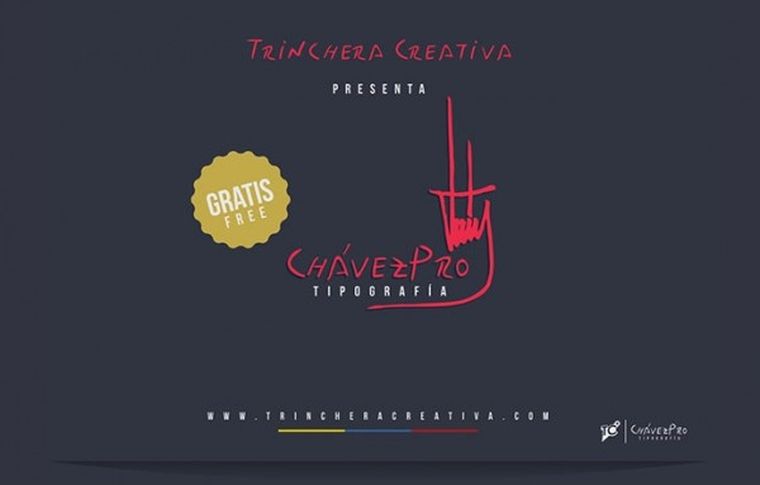
Idolatría: crearon una fuente tipográfica con la letra de Chávez
El fallecido presidente de Venezuela Hugo Chávezhabría cumplido hoy 60 años y sus seguidores se empeñan en mantener vivo su legado, ideas e incluso presencia. Algunos de ellos han deseado tanto que su líder continúe escribiendo que han desarrollado una tipografía inspirada en el ex presidente venezolano.
La fuente TC ChávezPro ya puede incorporarse al menú de cualquier procesador de textos convirtiendo el nombre del denominado líder bolivariano en una más de las opciones de escritura del menú junto a los clásicos Times New Roman o Arial, según lo publicó en su portal digital el diario peruano El Comercio.
La idea surgió de un grupo chavista denominado Trinchera Creativa, un colectivo que ofrece la opción de descargar la fuente desde supágina web.
La tipografía imita la letra del zurdo político, cuya firma es ya parte habitual en camisetas, gorras, llaveros y cuanto artilugio publicitario se vende en Venezuela con su imagen. Cabe resaltar que la comercialización de objetos relacionados con el promotor del Socialismo del Siglo XXI es más que prolífica.
Y para ese tipo de proyectos, esta nueva letra será una ayuda inestimable, según indicó el diseñador Marco Volpe, creador de la fuente. Volpe aseguró que quiso hacer un regalo a los seguidores deChávez en su cumpleaños y también a quienes trabajan con su imagen.
"La idea más que todo está hecha para diseñadores que quieran realizar arte con la letra del comandante", indicó el joven de 26 años que encabeza Trinchera Creativa.
El artista comenzó a darle vueltas a la idea de crear una fuente con la letra de Chávez hace dos años, cuando se tatuó el lema "Hasta la victoria siempre" con la particular escritura del comandante.
Volpe hizo un trabajo de investigación rastreando las cartas que escribió Chávez durante su estancia en la cárcel de Yare, donde cumplió prisión tras el fallido golpe de Estado de 1992, y la nota que envió para declarar que no había renunciado durante el intento de golpe en su contra de 2002.
De esa manera consiguió revisar las letras, seleccionarlas y hacerse el tatuaje entonces.
"Hace un mes y medio fue que retomé la idea para dárselo como regalo al comandante y, bueno, a la gente", explicó.
Volpe comentó que tuvo que investigar bastante sobre la escritura de Chávez y hacer un trabajo comparativo porque "hay letras que no escribía siempre igual, a veces escribía con letra más grande, de manera diferente".
"Agarré las letras más parecidas de cada una", señaló el promotor de Trinchera Creativa, sitio web que nació como proyecto hace tres años, como una ventana de apoyo al proceso bolivariano desde una estética pop y minimalista, reflejando críticas y también los resultados del proceso bolivariano como las misiones sociales, señaló.
La letra de Chávez se suma así a la prolífica industria surgida en torno a su figura.
La ChávezPro deja además varios regalos a los seguidores de Chávez, fallecido el 5 de marzo del año pasado tras un cáncer que acabó con su vida en 20 meses.
Con combinaciones de mayúsculas sobre las teclas de la almohadilla o de la barra aparecen frases célebres de Chávez como "por ahora y para siempre" o "hasta la victoria siempre". En la arroba aparece la firma de Chávez.